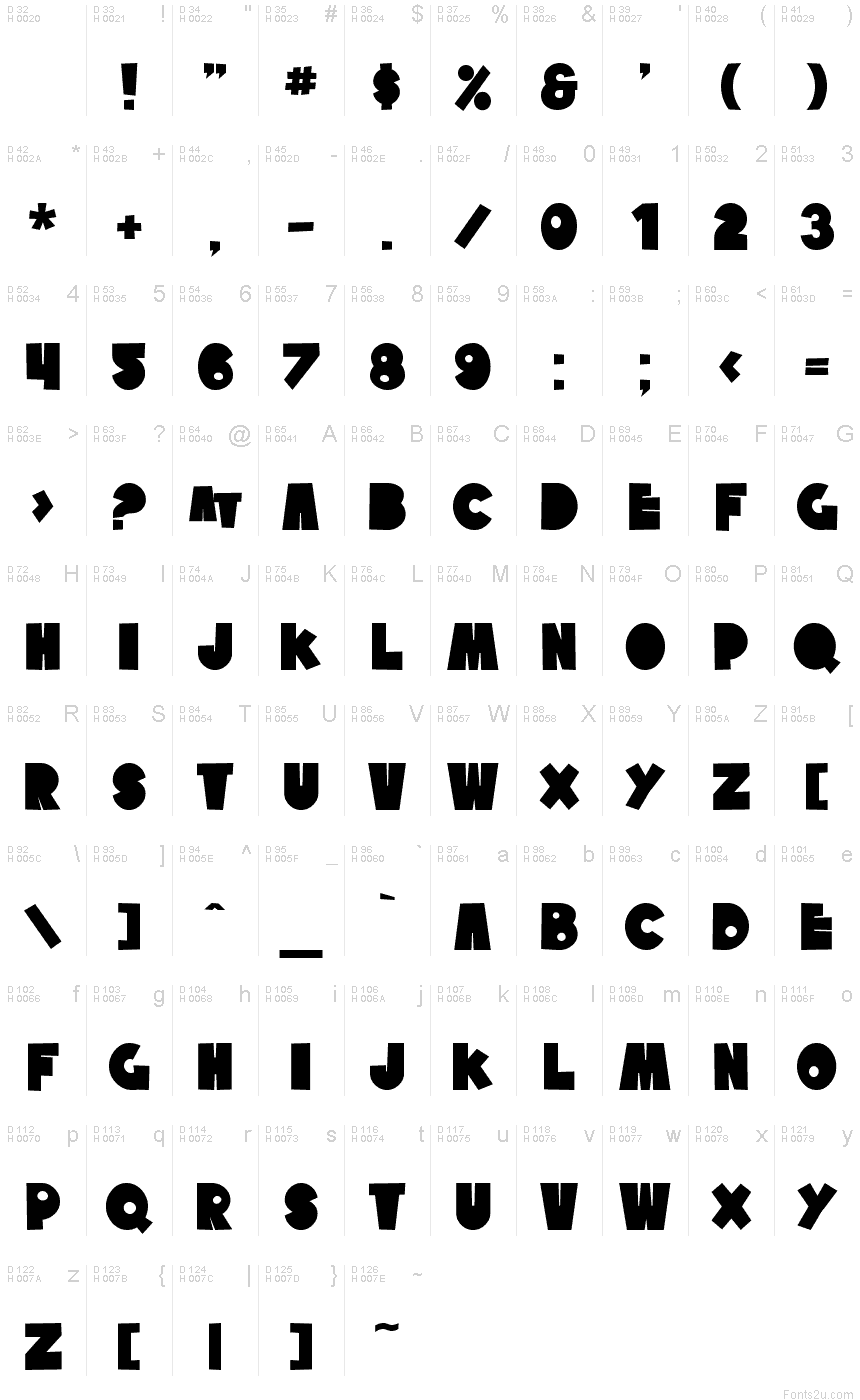
Vorschau der Schriftart SF Tattle Tales Bold
SF Tattle Tales Bold von ShyFonts Type Foundry ist eine kostenlose Comic-Display-Schrift mit markanten, vollflächigen Großbuchstaben, die wirken, als wären sie aus Papier ausgeschnitten und direkt in ein Cartoon-Cover geklebt worden. Die Buchstaben setzen auf stumpfe Keile, unkonventionelle Winkel und leicht unebene Breiten, was dem Alphabet eine lebhafte, erzählerische Dynamik verleiht – statt einer steifen, geometrischen Anordnung.
Das macht diese kostenlose Schrift zur idealen Wahl für Kinderbuchcover, Comic-Überschriften, Plakate für den Unterricht, verspielte Verpackungen und kurze Titelkarten, bei denen die massiven Buchstaben sofort ins Auge fallen. Sie eignet sich auch hervorragend für Monogramme und Initialen, da die Formen simpel, aber keineswegs langweilig sind und gerade genug Unregelmäßigkeit besitzen, um selbst einen einzelnen Buchstaben lebendig wirken zu lassen.